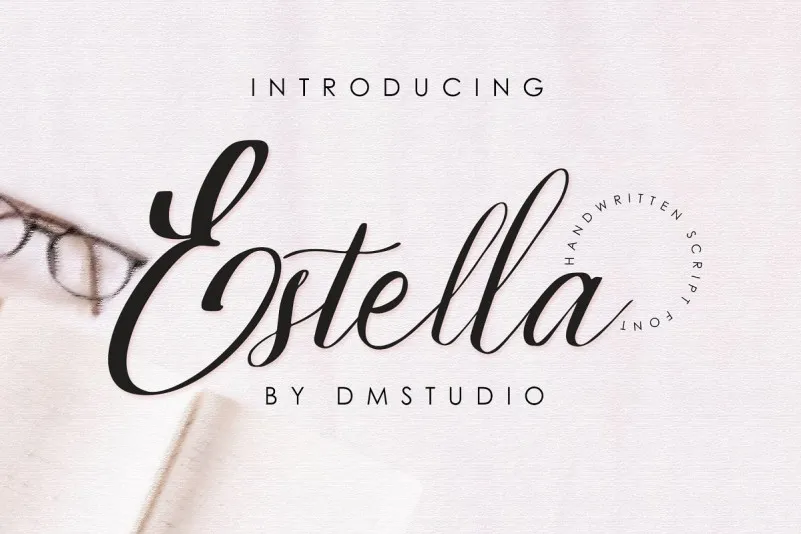
Estella Script Font – Download Grátis
A Estella Script Font é uma nova fonte tipográfica à base de script que vem trazer um toque refinado para quem precisa de elegância nas próximas criações. Esta font foi especialmente concebida para aqueles designers que desejam adicionar algo único e incrível a seus projetos, proporcionando resultados perfeitos. Com seu design cuidadosamente elaborado, a Estella está pronta para destacar o belo da sua obra de arte. Você pode usá-la em um lema, cartão de logotipo, embalagens, título, poster, camisetas ou roupas, cartões de cumprimentos e até mesmo convites de casamento. Com a Estella Script Font na sua mesa, seu trabalho terá uma resolução e sofisticação que o torna único. Não se esqueça de experimentar diferentes aplicativos da fonte para encontrar o melhor resultado – seja em um logo profissional ou em cartões personalizados. Eles sempre farão a diferença!